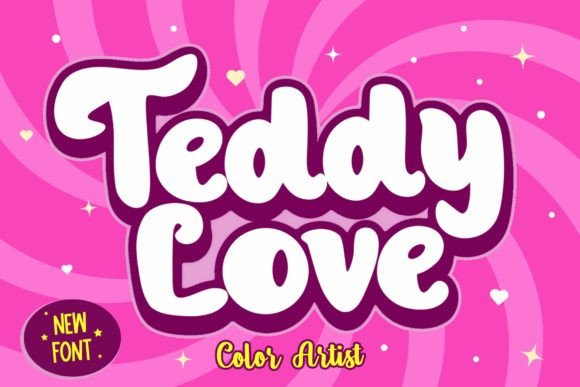
Teddy Love
適切なデザイン要素を見つけるのは難しい場合がありますが、Teddy Loveは作品を即座に引き立てる優れたコレクションを提供します。
POD(オンデマンド印刷)製品、結婚式の招待状、またはソーシャルメディアのグラフィックを作成している場合でも、Teddy Loveは理想的です。